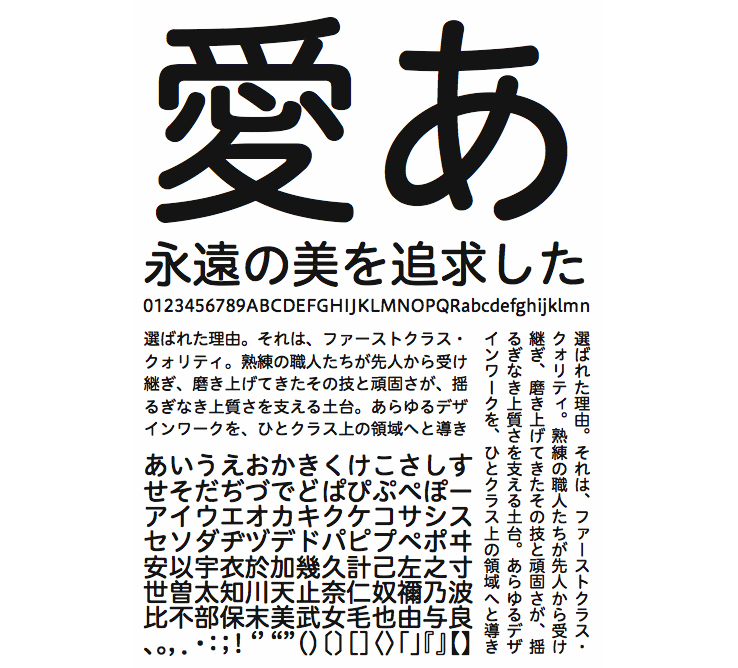
【ヒラギノUD丸ゴ】「ヒラギノ丸ゴ」の基本デザインを受け継ぐユニバーサルデザインのフォントです。やや小さめの字面で仮名には柔らな骨格を採用。濁点・半濁点の強調、数字・欧文のオリジナルデザイン採用により判読性を向上。美しいデザイン性と長い文章も心地よく読める可読性を提供。雑誌、Web、サイン、TVテロップなど幅広い用途に対応。印刷でもディスプレイ表示でも、縦組でも横組でも美しい組版を実現します。
ヒラギノUD丸ゴ StdN W5